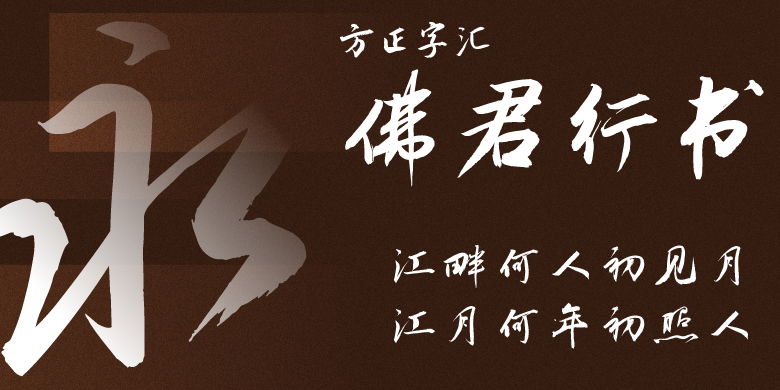
方正字汇-佛君行书
字体品牌: 方正字汇 设计师:李佛君 字体分类:创意书写 字体属性:精品字 字符集:大陆简体(GB2312-80) 发布时间: 2022
方正字汇-佛君行书,渊承二王,取意米蔡,书风凌厉,强调书写的连贯气息,淋漓畅快,结体奇骏险绝,笔意俊逸,用笔奔放,挥洒自如,适用于各类平面视觉、产品包装、广告宣传、报刊标题、文化艺术等用途。